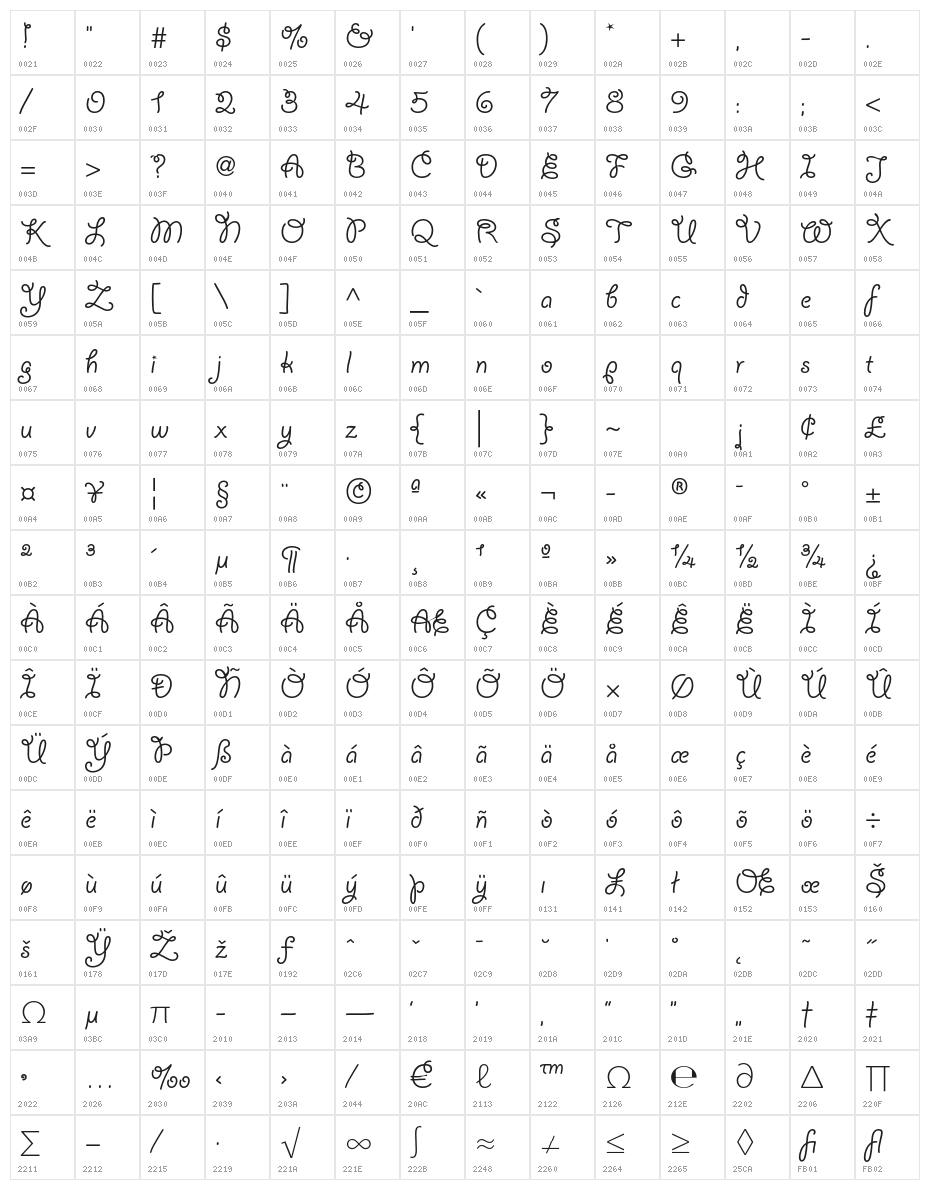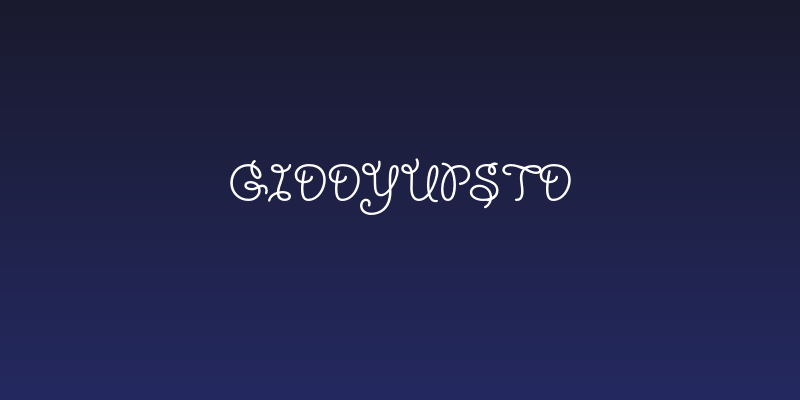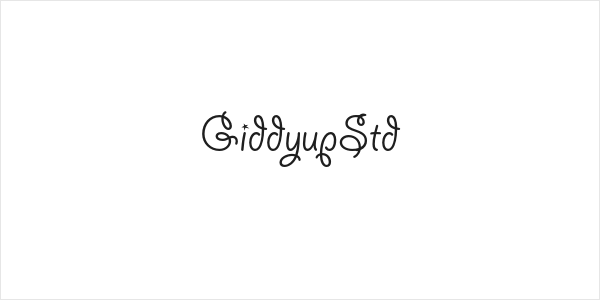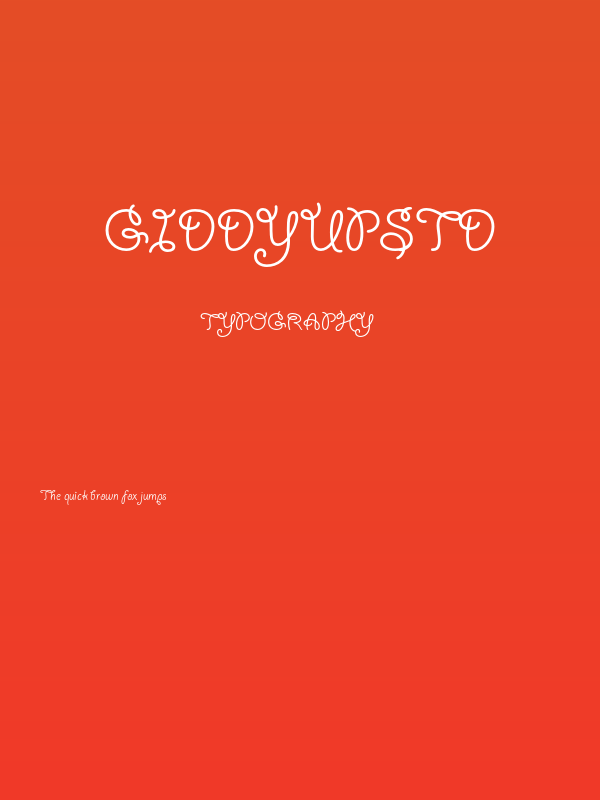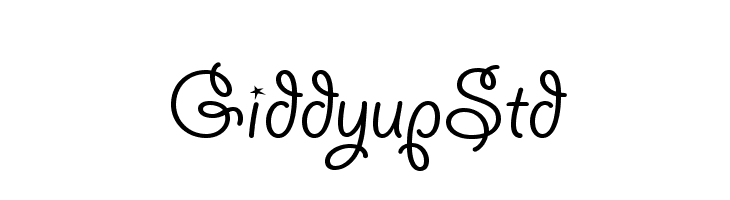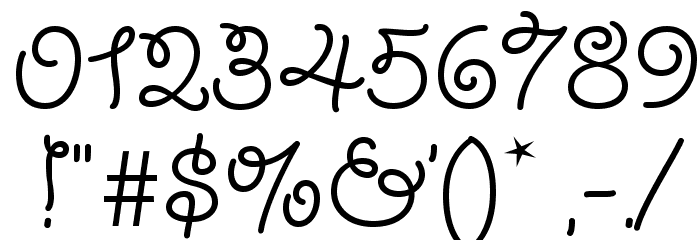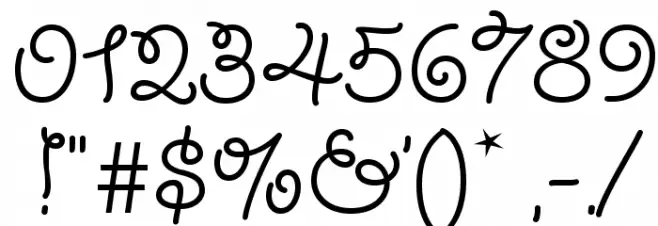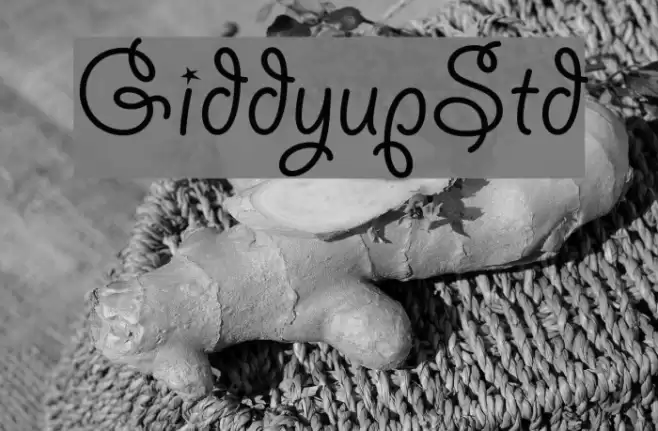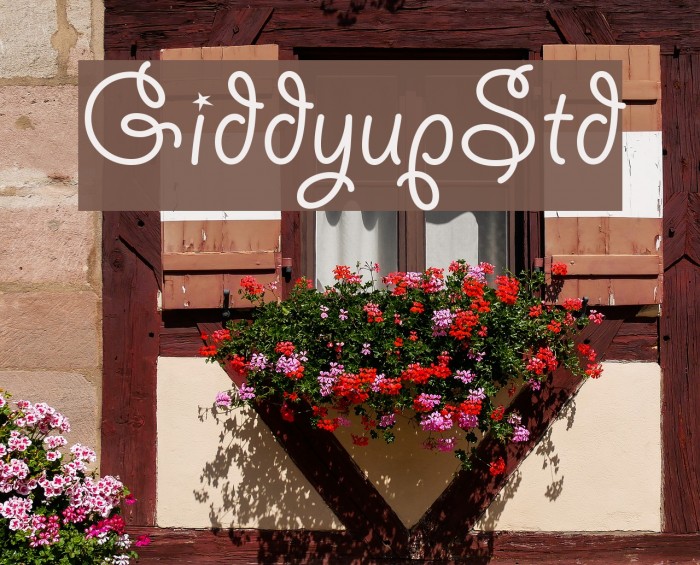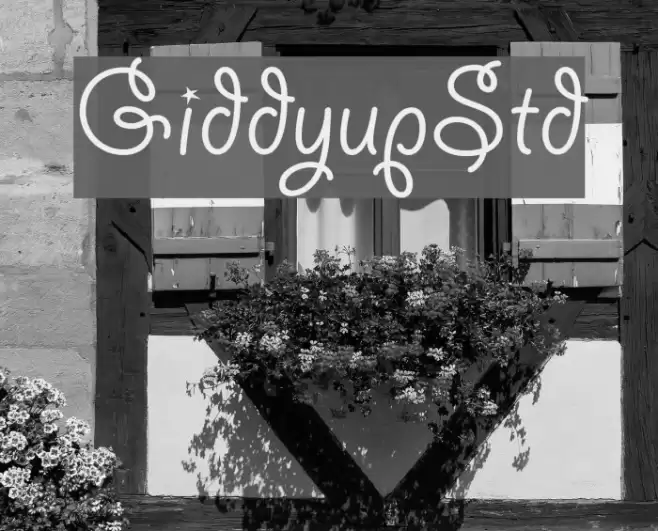
GiddyupStd Font
| Estilo geral | Playful, Whimsical |
| Caso de uso | Headlines, Logos, Decorative Text |
| Projetos propostos | Ideal for children's book covers, playful branding, greeting cards, and party invitations. |
| Autor | Fonts by Iconian Fonts |